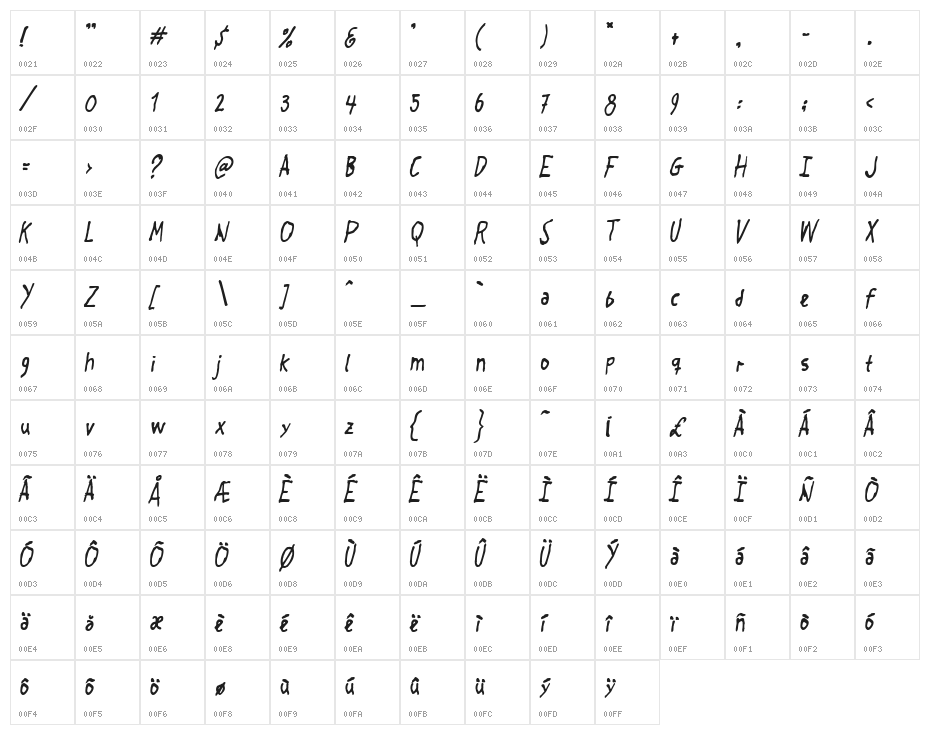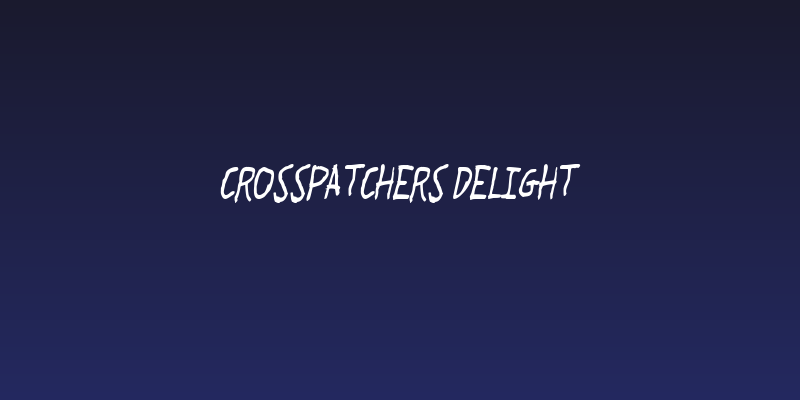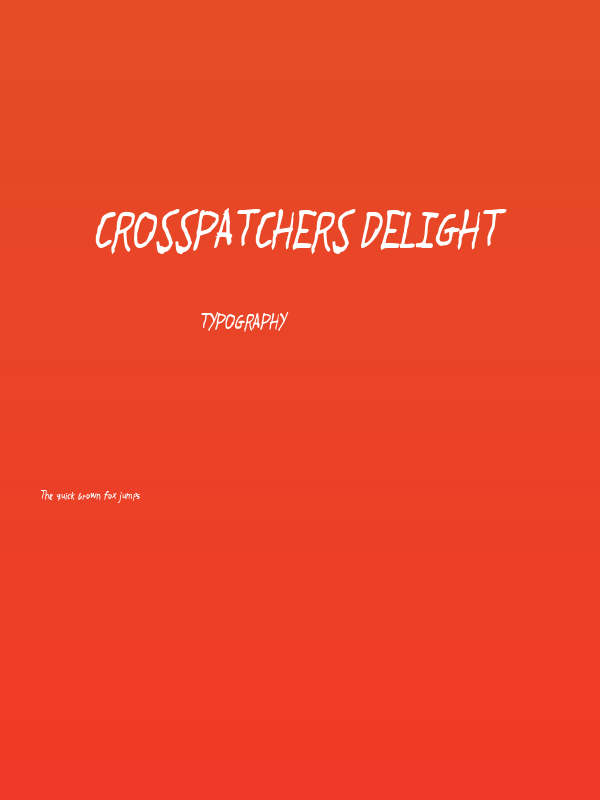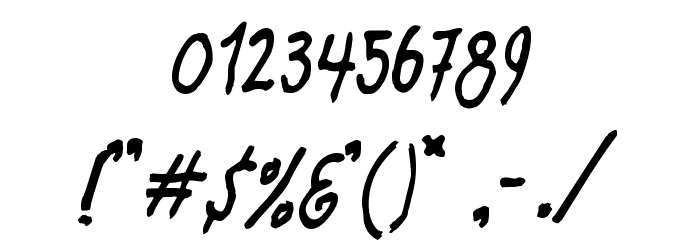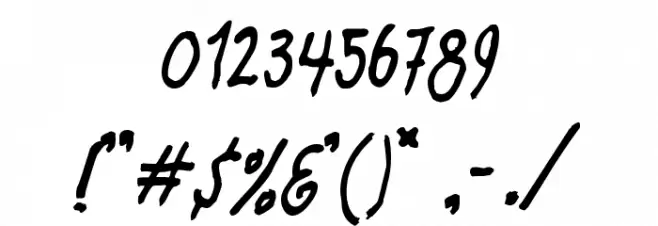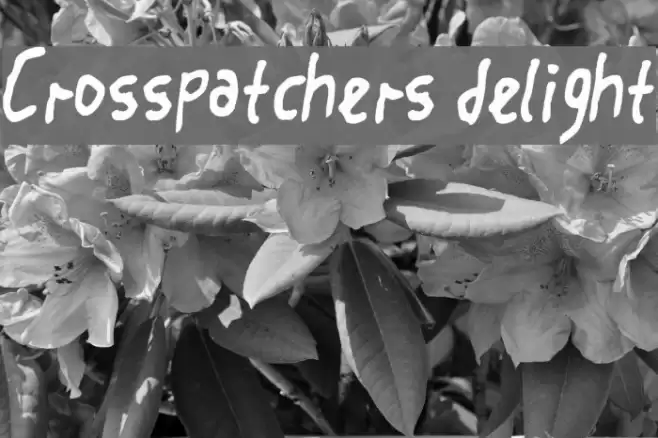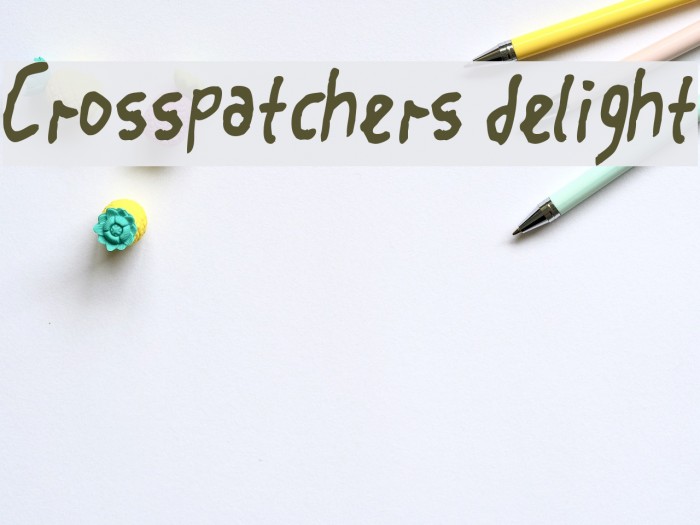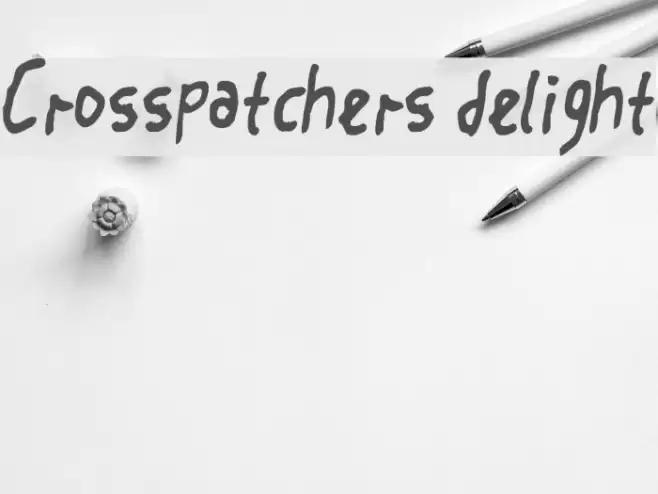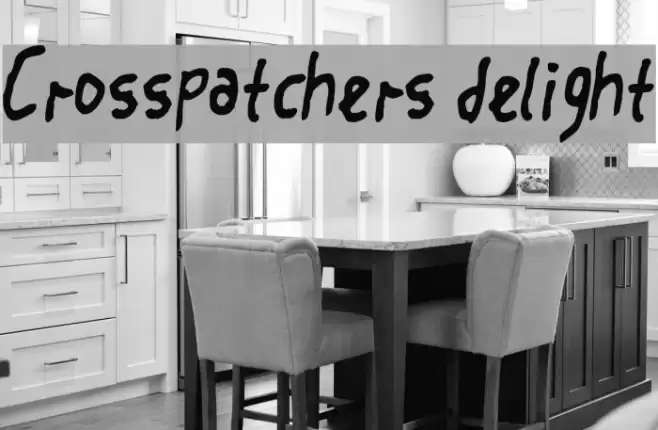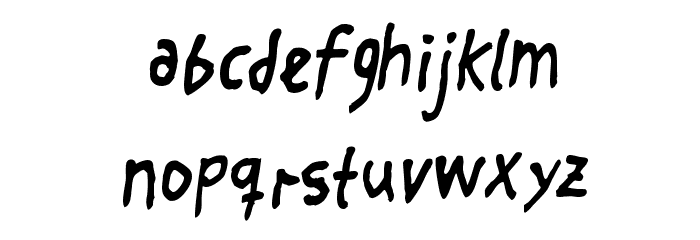
Crosspatchers delight Font
✎ Quirky
| Kategorien | Quirky |
| Gesamtstil | Casual, Playful |
| Anwendungsfall | Headlines, Logos, Creative projects |
| Vorgeschlagene Projekte | Ideal for greeting cards, children's books, casual branding, and creative posters. |